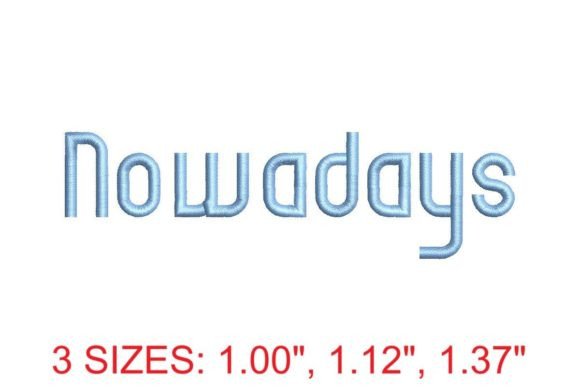
Nowadays Font
Nowadays Fontのような高品質の素材をお探しの場合、このプレミアムパッケージはクリエイティブなプロジェクトに素晴らしい選択です。
POD(オンデマンド印刷)製品、結婚式の招待状、またはソーシャルメディアのグラフィックを作成している場合でも、Nowadays Fontは理想的です。